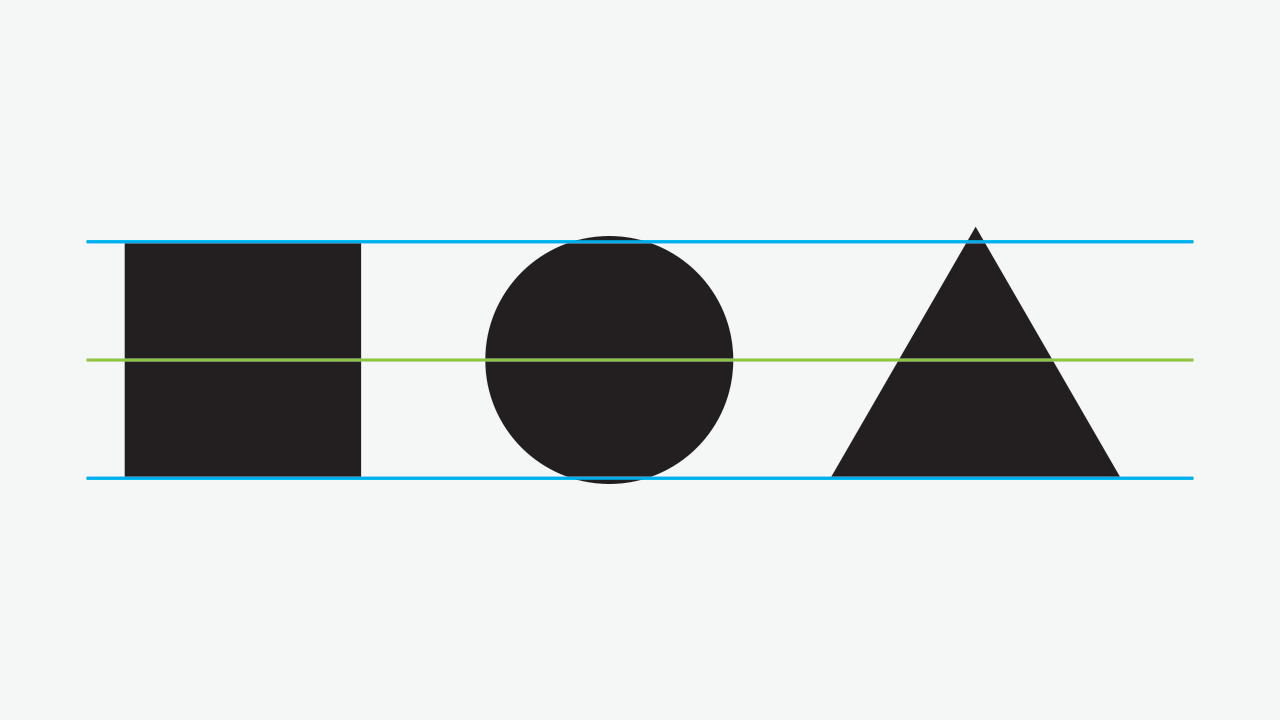
Warum stehen bei der Futura die Spitzen über?
Bei der Futura stehen in Großbuchstaben die Spitzen "über", also beim N, M, A usw.
Ist das eine rein ästhetische Entscheidung von Paul Renner gewesen? Ich habe mal gelesen, dass es irgendetwas mit dem Druckverfahren zu tun hatte, kann den Link aber leider nicht mehr finden :( .